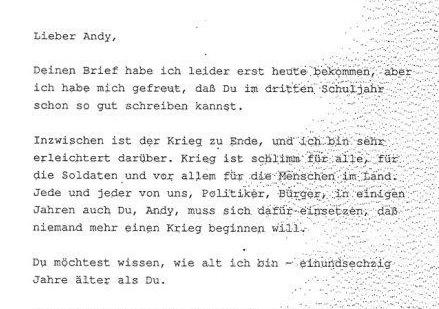
Frage Schrift Schreibmaschine
wer kann mir sagen, welche Schrift hier verwendet wurde?
Sorry für die schlechte Qualität!
Achja, das Schreiben ist von 1991.
Das ist die Antwort von Richard von Weizsäcker an einen Drittklässler, der ihm Anfang der 90er geschrieben hat. Ich schreibe morgen über diesen Brief und mir war als Detail die Schriftart wichtig. Will mich da nicht blamieren und die falsche angeben - dann heißt es wieder "Lügenpresse" ;-)
Meinst du nicht auch, das in diesem Zusammenhang die Tatsache, das es sich mit großer Wahrscheinlichlkeit um einer der bei Schreibmaschinen weit verbreiteten Courier-Varianten handelt, das absolut unwichtigste an diesem Brief ist? Es ist doch einfach nur die Schreibmaschinen-Schrift, welche in der Schreibmaschine der Schreibkraft Richard v. Weizsäckers zur Verfügung stand. Auch alle weiteren typografischen Eigenschaften ergeben sich schlicht aus der vorhandenen Schreibmaschine, und dem üblichen Papierformat A4.
Kaum jemand kann auch sagen, welche Schreibmaschine im Büro Weizsäckers verwendet wurde, ob nun eine von Adler, Olympia, Olivetti, IBM oder wer weiß? Eine IBM Kugelkopf-Maschine ist, da in besseren Büros recht verbreitet, ist wahrscheinlich. Hier ähnelt dann das Schriftbild der Courier 12.
Natürlich ist es das absolut Unwichtigste, oft sind es aber so kleine Details, die eine Geschichte "farbig" machen, etwa auch, welches Getränk bei einem Gipfel serviert ("Sie tranken Earl Grey und sprachen über Abrüstung") oder mit welchem Füllfederhalter ein Friedensvertrag unterschrieben wurde :)
PS: Und DIE müssen dann aber stimmen. Stell dir vor, jemand schreibt dann, das sei die Schriftart "Arial" - dann gibt es garantiert jemanden, der sich damit auskennt und nur den Kopf schüttelt über so viel Unwissen bzw. mangelnde Recherche.
Kaum jemand kann auch sagen, welche Schreibmaschine im Büro Weizsäckers verwendet wurde, ob nun eine von Adler, Olympia, Olivetti, IBM oder wer weiß? Eine IBM Kugelkopf-Maschine ist, da in besseren Büros recht verbreitet, ist wahrscheinlich.
Widerspruch, Herr College. Da sogar ich 1991 meine Briefe am Mac geschrieben habe, wird das Bundespräsidialkontor sicher auch Rechner verwendet haben und keine Schreibmaschinen. Und die Courier war ja (zumindest am Mac, aber sicher auch an DOS-Rechnern) so ziemlich von Anfang an am Start, 1990ff auf jeden Fall.
Das ist die Antwort von Richard von Weizsäcker an einen Drittklässler, der ihm Anfang der 90er geschrieben hat. Ich schreibe morgen über diesen Brief und mir war als Detail die Schriftart wichtig. Will mich da nicht blamieren und die falsche angeben - dann heißt es wieder "Lügenpresse" ;-)
Einspruch abgewiesen, Herr Kollege! Richtig, das 1991 der Apple Mac heraus kam. Nur waren in Politikerbüros eben, gerade wegen der noch deutlich beseren Schriftqualität mit Cabonband und Kugelkopf in vielen Büros die Schreibmaschine noch das vorherrschende Schreibgerät. Damals, also in der Zeit. Macs waren - und sind ja auch eher im grafischen Gewerbe daheim,
der 80286 für den XT-PC kam ja auch erst 1982 auf den Markt, An Vektorschriften im Büro war auch noch nicht zu denken MS-Dos hatte zwar eine Courier, diue war aber eine recht grobe Pixelschrift, der Ausdruck weit ab von Letter-Qualität.
Zudem verwendete man, hatte man einen PC und einen sauteuren 24-Nadler (und das dann auch erst 1995) dann auch mit einer proportionalen Schrift, und ahmte nur dann eine Schreibmaschine nach, wenn wegen Tabellen eine nicht proportionale Schrift, und damit eben die Courier nötig war.
Doch doch, das ging schon. Ich habe 1989/90 kurzzeitig an einem Dos-Rechner mit Pagemaker gesessen, der mit einem Laserdrucker gekoppelt optische Druckvorlagen erstellt hat. Das war damals noch ziemlich teuer (irgendwie fünfstellig), aber der Gedanke, daß diese Technik ein, zwei Jahre später auf Bellevue verfügbar gewesen sein muß, ist durchaus naheliegend. Der HP Laserjet war immerhin seit 1984 auf dem Markt. Wir haben also im fraglichen Zeitraum alle technischen Komponenten und die fragliche Schrift verfügbar und eine Behörde, der es sicher nicht an ein paar tausend Mark gefehlt hat, um eine effiziente Bureauorganisation mit optisch ansprechendem Output zu unterhalten.
Ich fürchte, dass man das ohne Insiderwissen nicht extrapolieren kann. Ich kenne Behörden und sogar Uni-Büros, in denen noch bis in die zweite Hälfte der 90er auf Schreibmaschinen geschrieben wurde. Den Sachbearbeiterinnen und Sekretärinnen waren diese Computer oft nicht so richtig geheuer und das Schreiben auf Schreibmaschinen ging ihnen flotter und fehlerfreier von der Hand.
Das Bundespräsidialamt lebt ja ein bisschen in einer Welt für sich. Da es nicht so den tagespolitischen Unwägbarkeiten ausgesetzt ist wie andere Behörden, wäre vielleicht mehr Spielraum da gewesen, um früh mit neuer Technik zu experimentieren und Mitarbeiter zu schulen. Andererseits gab es aber bestimmt auch nicht solch hohen Druck, durch Computereinsatz effizienter zu arbeiten. Ohnehin kann ich mir gut vorstellen, dass es für eine erfahrene Schreibkraft erheblich effizienter war, individuelle Höflichkeitsbriefe auf der Schreibmaschine zu schreiben als am Computer. Ein Blatt Papier einzuziehen und einen Text zu tippen ging einer fehlerfrei tippenden Schreibkraft nun mal schneller von der Hand als: